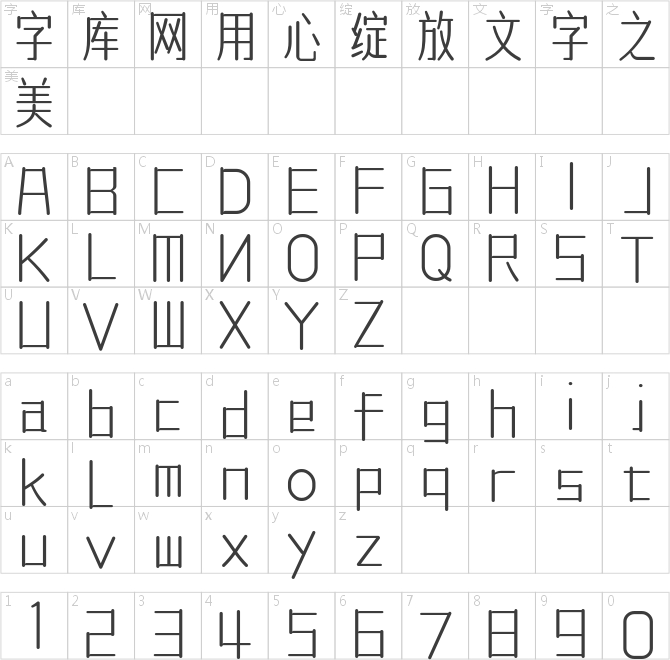
字体名称: 字体传奇南安体
字体传奇南安体
字体传奇南安体-是字体传奇网字友-吴金彬设计-字体传奇编码完成的一套免费商用字体,字体的起名是吴金彬以他的家乡南安命名的,他把这款字体,贡献给大家永久免费商用,也希望大家记住吴金彬和他的家乡南安。
字体传奇南安体字体字库是一款让人赏心悦目、百看不厌的中文字体,适合各类广告和产品包装设计应用,字体大小4.73MB,格式为ttf字体,上传用户是……西央,作者/版权方为字体传奇